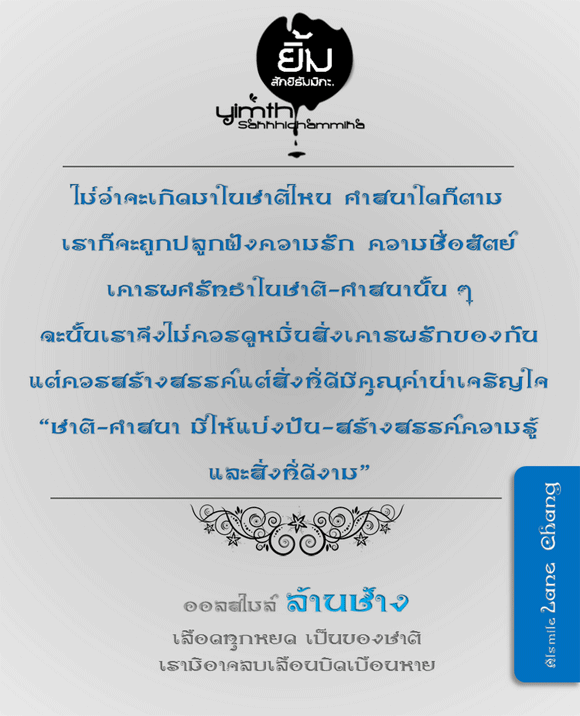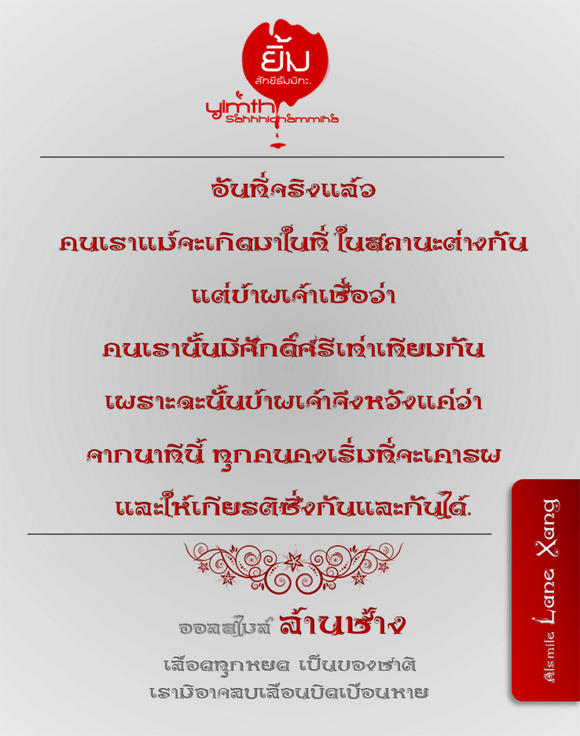
Alsmile Lane Chang และ Alsmile Lane Xang
ฟอนต์ “ออลสไมล์ ล้านช้าง” ฟอนต์นี้มีลักษณะเฉพาะตัวที่เกิดจากความชื่นชอบใจของข้าพเจ้าเอง
แต่จะทำอย่างไร สไตล์ฟอนต์ก็ย่อมสะท้อนบุคลิก-ความเป็นมาของบุคคลที่ทำได้
จึงสรุปไว้ในคำว่า “เลือดทุกหยดเป็นของชาติ เรามิอาจลบเลือนบิดเบือนหาย”
เป็นฟอนต์ที่ทำขึ้นมาจากการฝึกเรียนรู้ที่จะบริโภคเทคโนโลยีด้วยปัญญา
ฟอนต์นี้เป็นการฝึกหัดทำ จึงอาจมีการพัฒนาปรับปรุงไปได้อีก หากข้าพเจ้าเห็นว่าจะทำต่อไปได้
หากนี่คือหนึ่งรูปแบบของการทำความดี